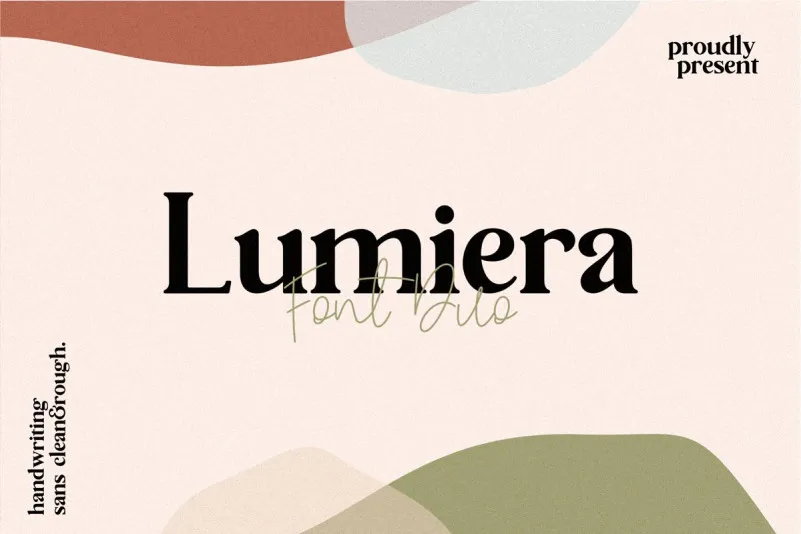
Lumiera Font Duo – Download Grátis
Lumiera é uma combinação perfeita entre um fontes simples sem serif e um tipo grande e bold, fornecendo um estilo elegante e luxuoso às suas criações de design. Esta font é ideal para elementos que buscam um toque moderno ou clássico, pois está disponível em várias variações – desde as linhas limpas e suaves até as tipografias escritas a mão com aparência áspera e macia. Com seu estilo simples sem serif, Lumiera oferece uma impressão de luxo moderna e sofisticada às suas publicações. Perfeito para capas de revistas, títulos de sites, selos master, convites, rótulos de design, logotipos, cartões de visita, currículos e outros produtos de design. Aproveite essa fonte imediatamente antes que o desconto termine.